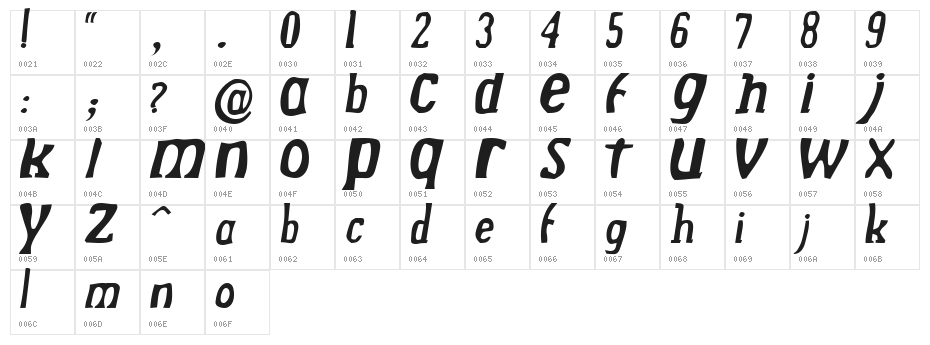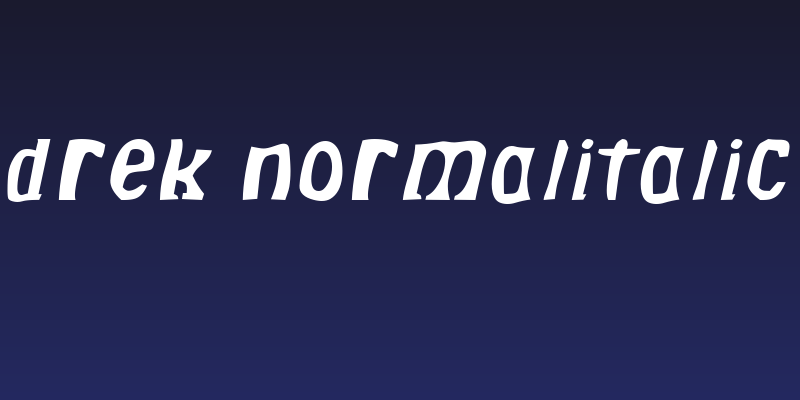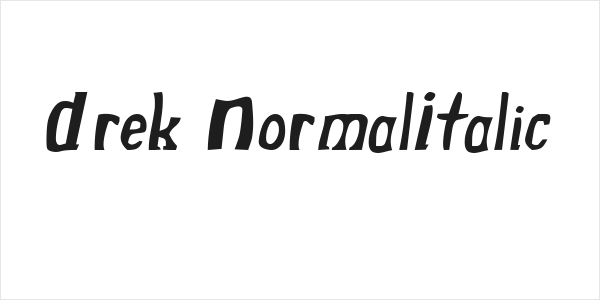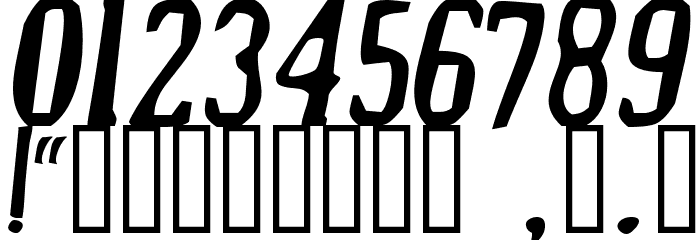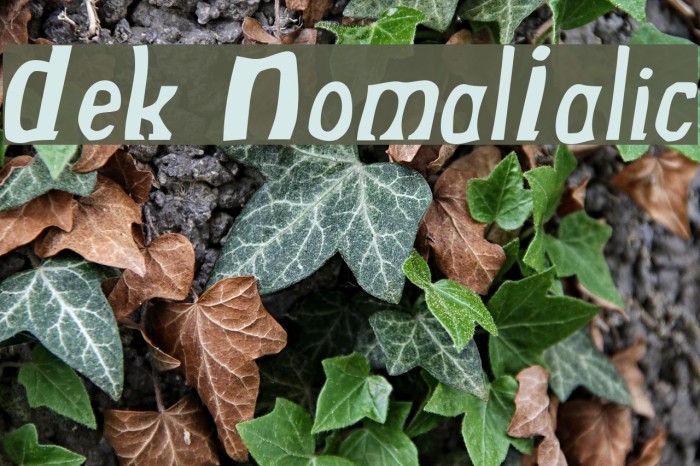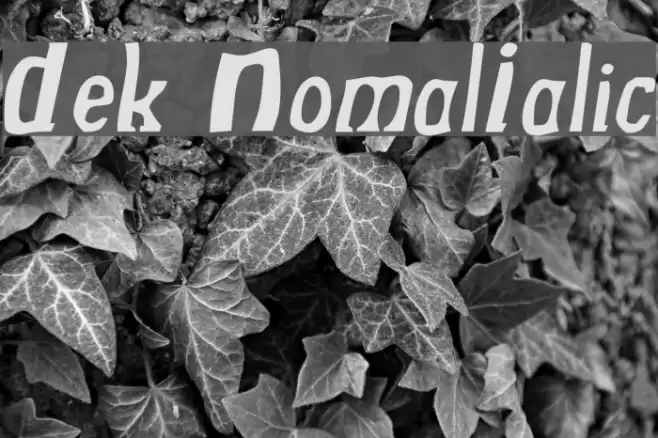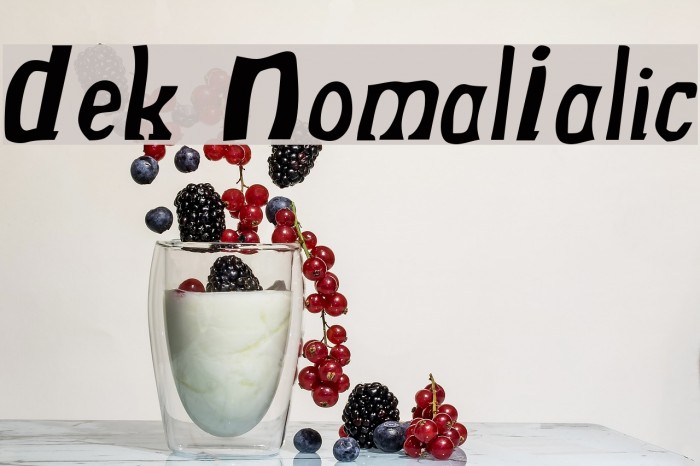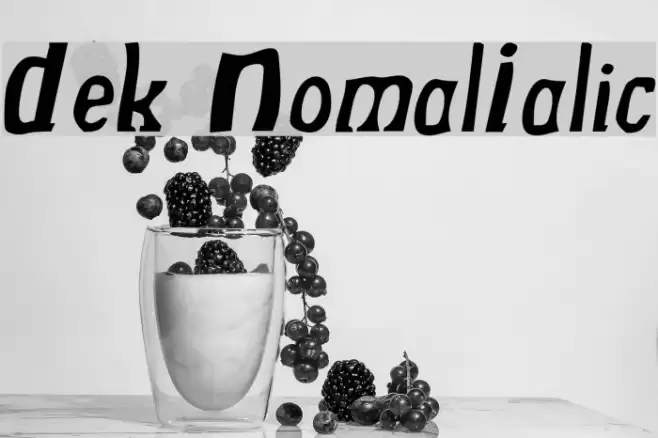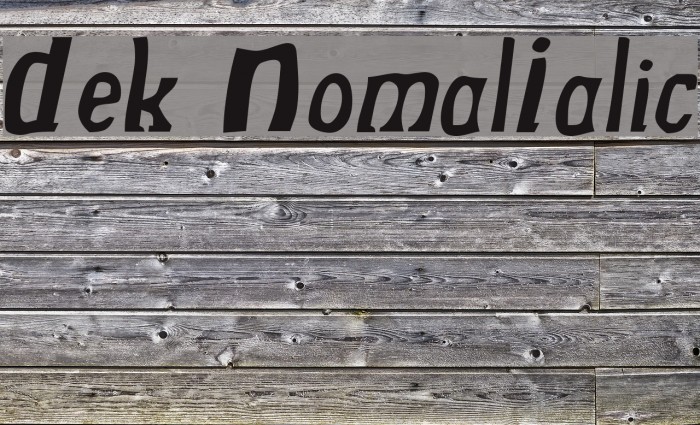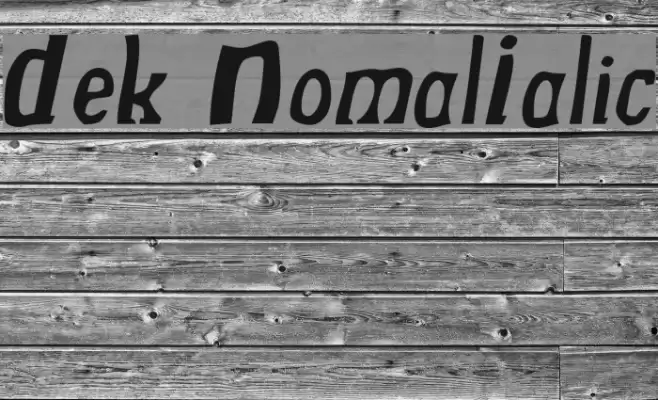
Drek NormalItalic Font
✎ Crazy
| Nome | Drek NormalItalic |
| Peso | NormalItalic |
| Categorie | Crazy |
| Progetti proposti | Ideal for branding, poster design, and headlines where a bold and modern look is desired. |